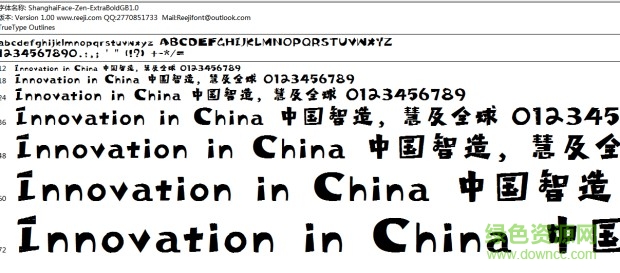
shanghaiface zen extraboldgb1.0和2.0兩款字體是綠色資源網(wǎng)為大家搜集的海派腔調(diào)禪大黑簡(jiǎn)合集下載包,結(jié)構(gòu)緊湊,疏密設(shè)計(jì)精巧,粗細(xì)對(duì)比強(qiáng)烈,非常有韻味,歡迎下載!
海派腔調(diào)禪大黑簡(jiǎn)特點(diǎn)
字體粗細(xì)度采用了粗的Bold的設(shè)計(jì),字形風(fēng)趣幽默,可以帶來(lái)全新的視覺(jué)體驗(yàn),夸張的筆畫(huà)設(shè)計(jì),筆畫(huà)對(duì)比強(qiáng)烈字與字大小差距較大,字體重心做了基本規(guī)范,部分字如海字采用凹凸不齊的邊緣來(lái)表達(dá)上海的海納百川的精神,全部字采用標(biāo)準(zhǔn)漢字的筆畫(huà)識(shí)別方法。